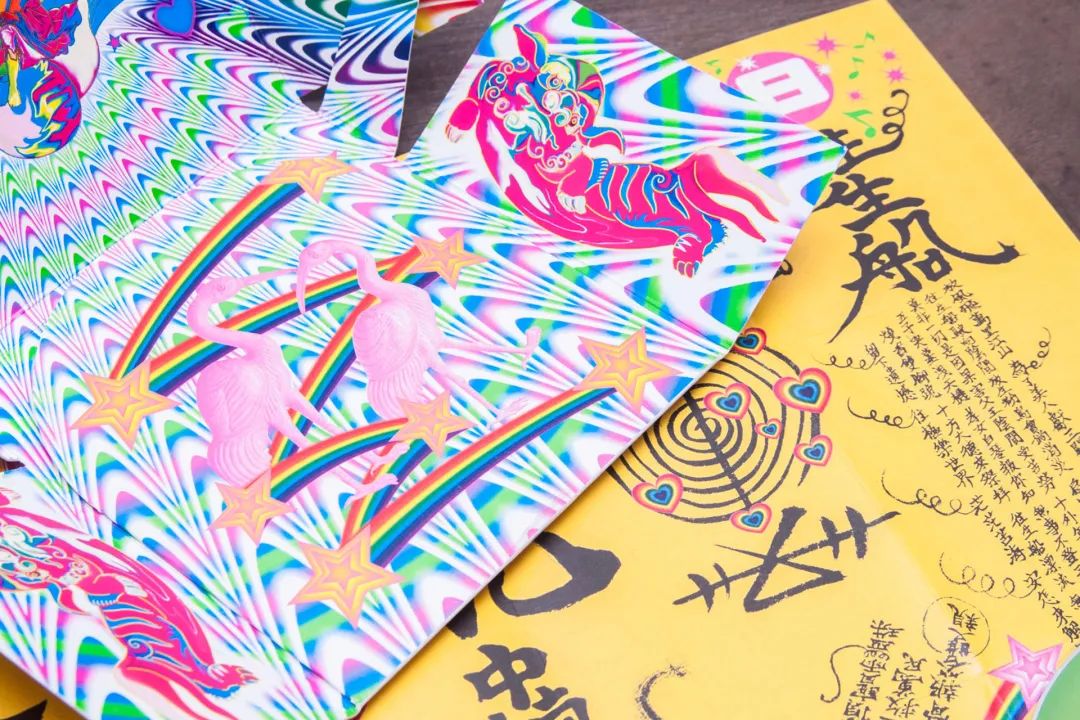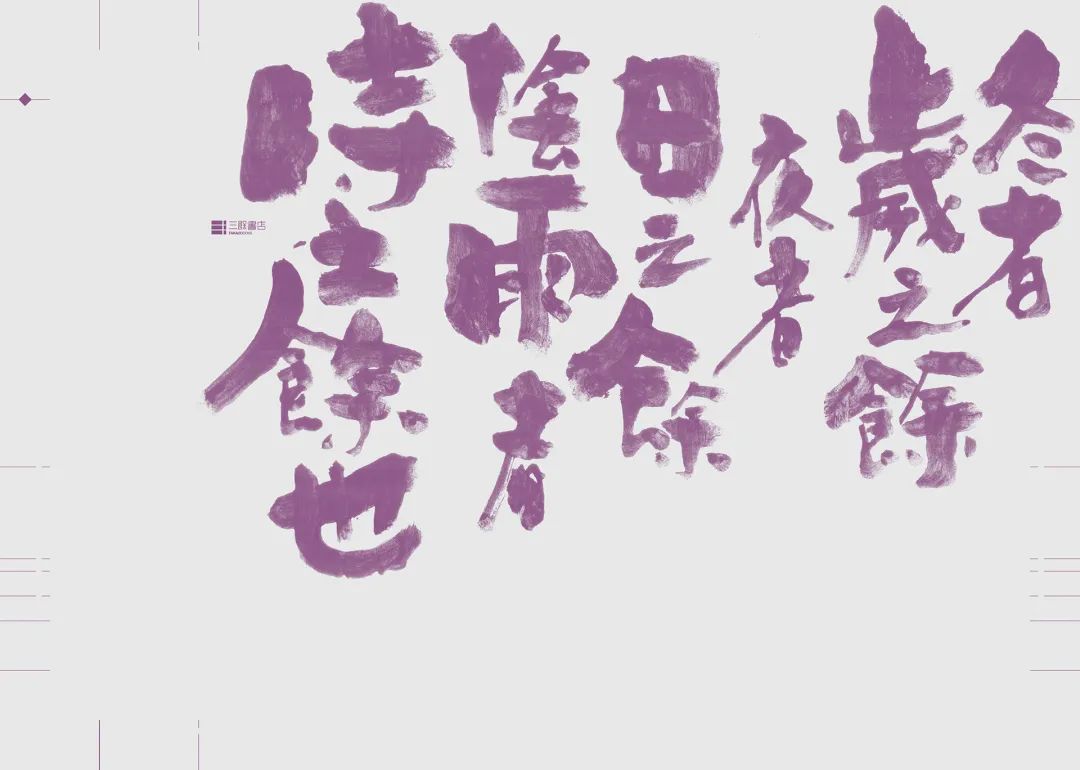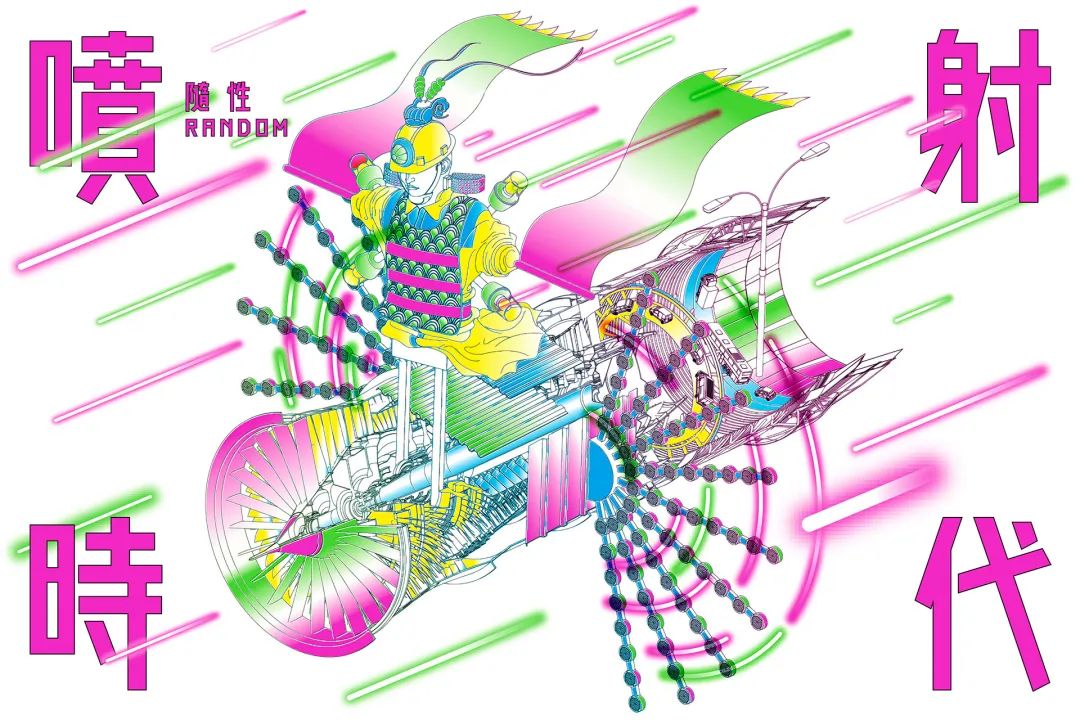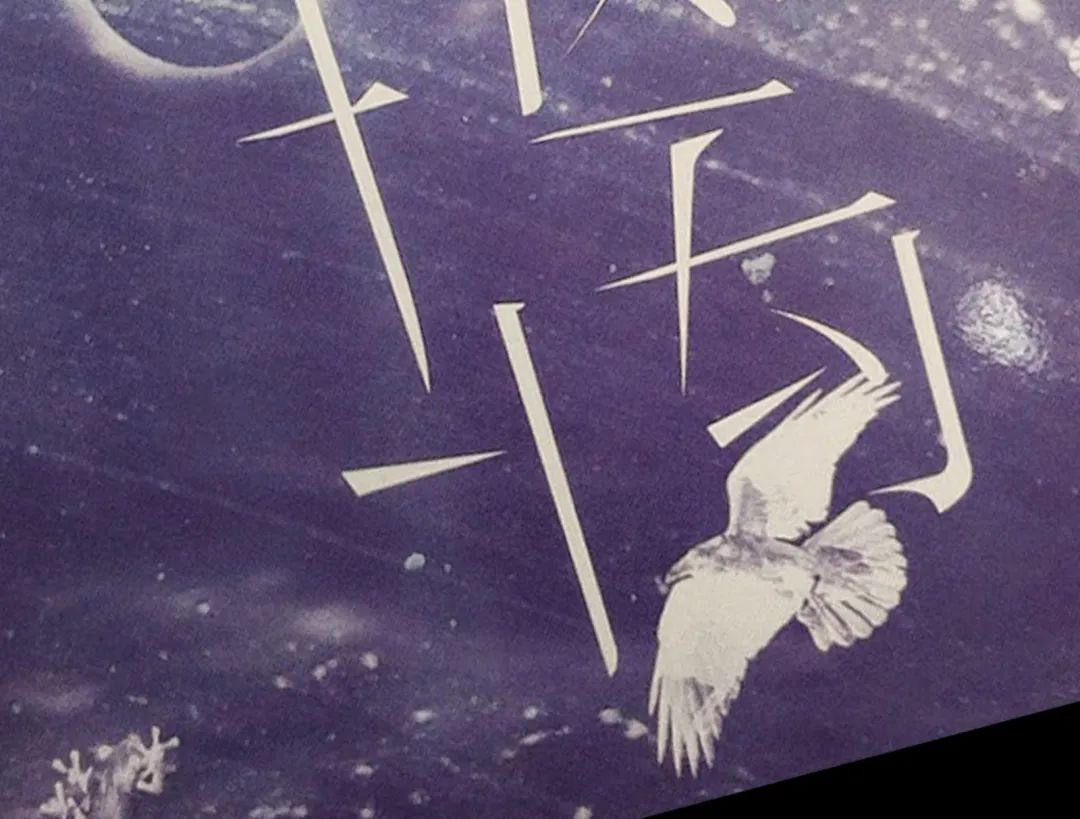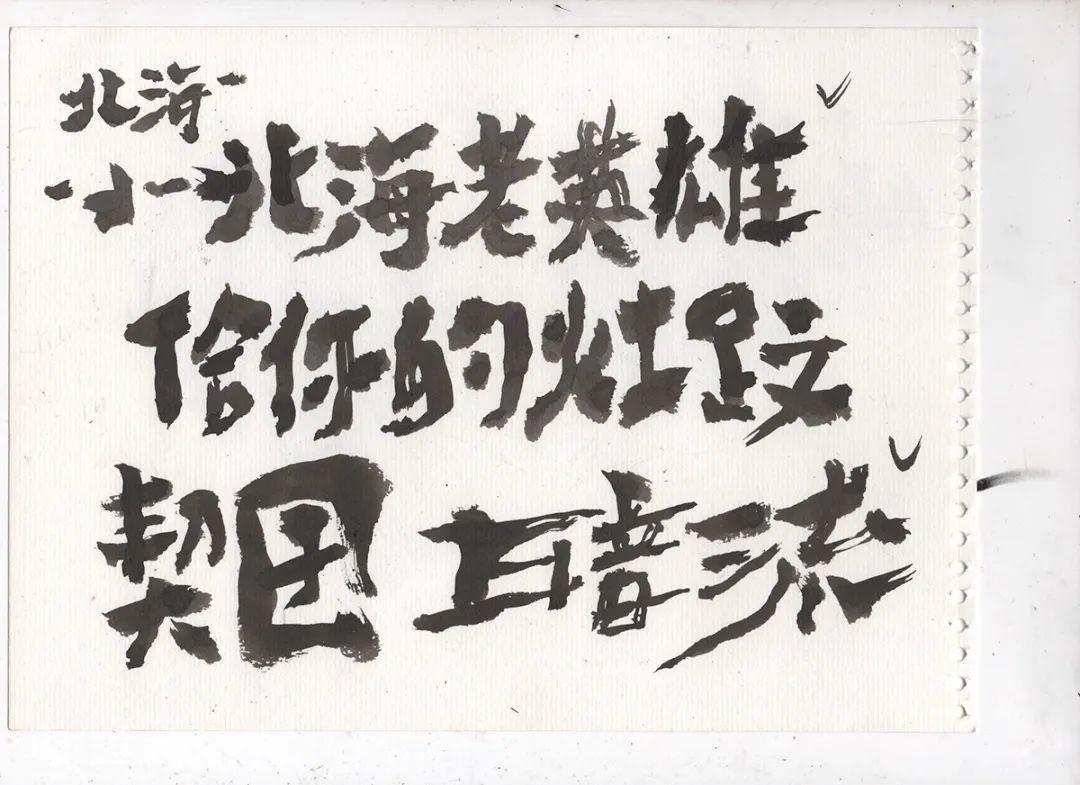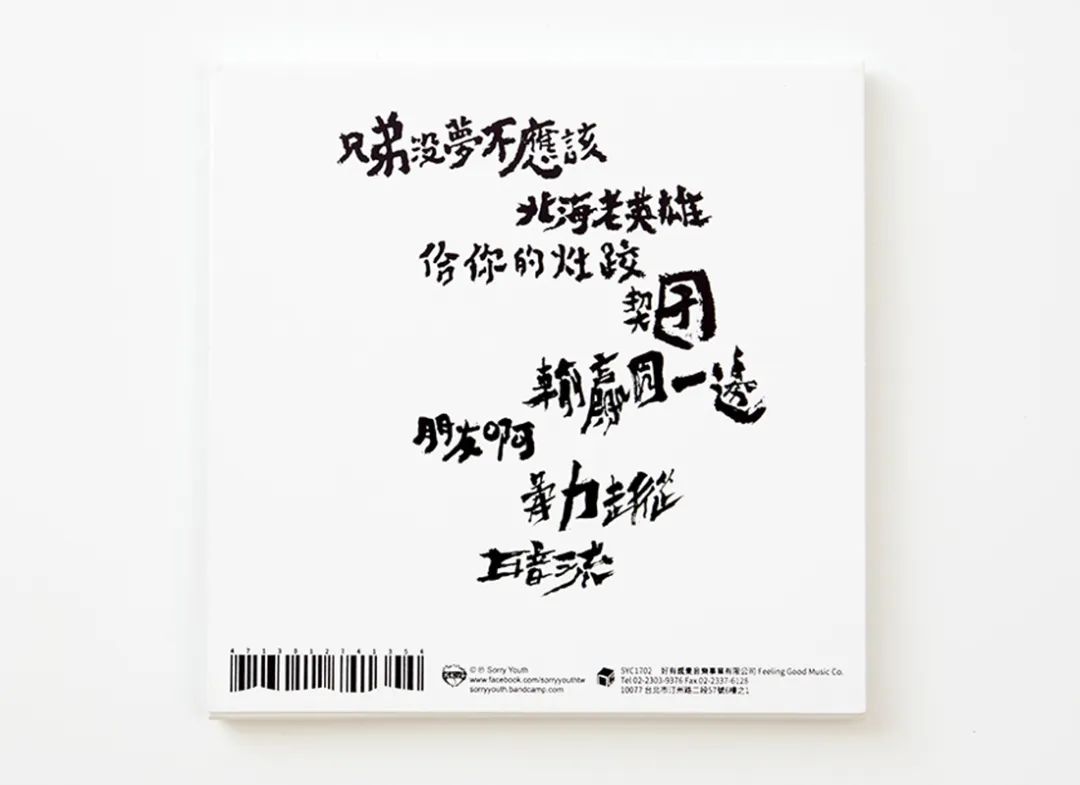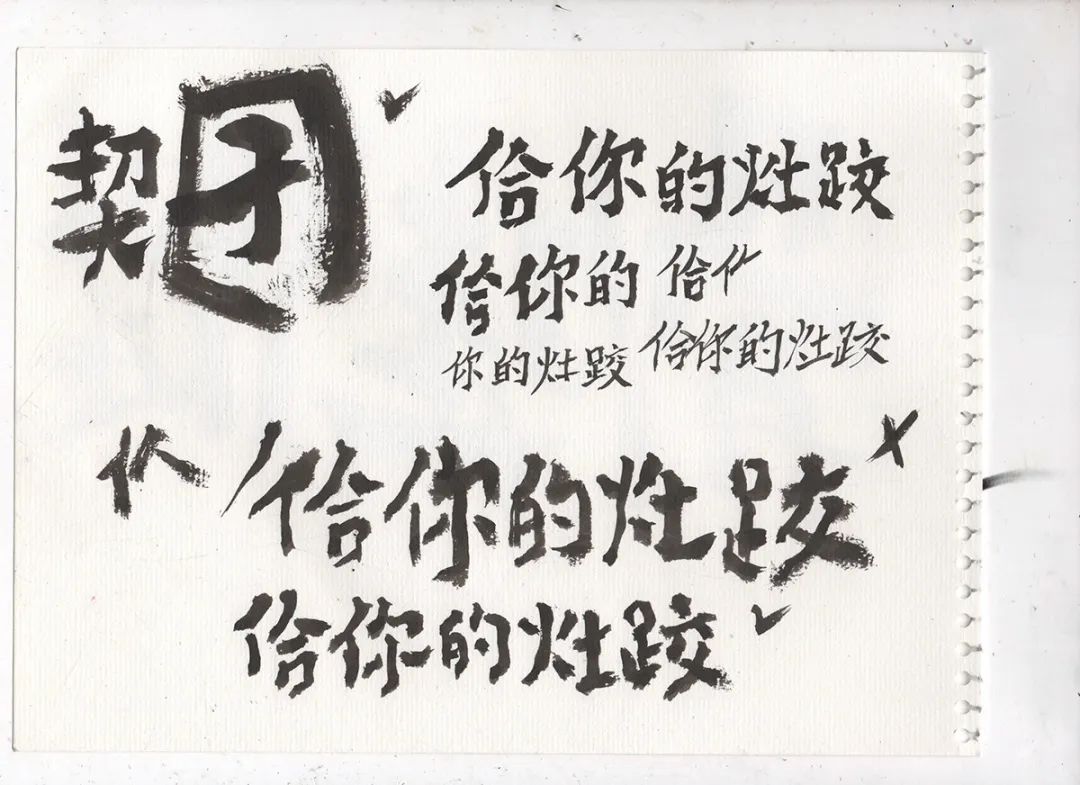
超大的字号、艳俗的色彩,他怎么这么秀
头顶板寸,脑后长辫,他身着大开三扣的花衬衫,脖子上的刺青会随着走路的摆动而忽隐忽现,我不说他是设计师的话,大家肯定会误以为是那条道上混的兄弟。这位张扬又粗犷的男子以他独特的「台味美学」混迹设计圈,他就是廖小子(本名廖俊裕),下面我们就一起来认识认识这个,痞气十足的设计师吧。
设计师简介
在台湾嘉义长大的廖俊裕,他的父亲是当地建筑工地的一个小型工程承包商,所以家中常有工人走动,那时廖俊裕的父亲对他说,要称这些人为「师傅」。打小起养成对手艺人的敬意,这让廖俊裕对劳动阶级多了一份深厚情感,这份难以割舍的感情,也成为他从台湾草根文化汲取创作养份的源头。
廖俊裕深受父亲的影响。现在袒露胸膛只扣一半花衬衫的打扮,也是耳濡目染了父亲的习惯。
从小他喜欢看功夫电影「好小子」,因此父亲开始叫他「小子」。就这样叫着叫着「廖俊裕」变成了「廖小子」。
高三时的一个领悟,使得廖小子背弃了父亲对他成为一名律师的期望。这可不得了,因为他们家族里有从事法律的亲戚,廖小子成绩也不错,做父亲的当然希望儿子能跟着去走法律的康庄大道。
然而廖小子执意要选美术系,因为这件事父子俩吵得非常凶,还在家里大打出手。两人拿着大型立式电扇互砸,最后「黑带三段」的儿子打赢了老子(真刚啊~)。无奈劝说没有,渐渐的廖小子的父亲就默许了这件事情。
有一次,廖小子的父亲喝醉了说:自己曾经也热爱绘画,但是没能坚持自己的理想,被你的祖父给劝退了,如果你真要转念美术系的话就要学好,要有决心在这条路上闯出一片天,也圆父亲的一个梦,自此廖小子就开始了他的设计之路。
高中毕业后,廖小子顺利的考上了高雄师范大学 ·美术系,但因家庭条件不好,连买画材的钱都没有,为了自力更生廖小子大学时就开始接活。跟大部分新手设计师一样,一开始接的都是些街头小广告,DM单之类的设计项目。那时的廖小子也喜欢日系、大气简单的设计,但是能发出这种委托的客户,想要什么东西大家心里都有数。
完成项目后,客户一直要求改稿,希望字可以在放的大一些、颜色要鲜艳的、图要修得很沙龙、在整个玫瑰顺带一个外框与阴影。
人在屋檐下不得不低头啊,最终廖小子选择了妥协说“既然打不过那就加入他”,而且要做就要做到自己满意为止。久而久之「把字放的很大」、「挑战文字装饰的可能性」等手法就变成了廖小子做设计的方式。
在一次的采访中,廖小子带著几分自豪的笑了笑说:后期因为习惯把字放的很大,使得我成为了第一位,让客户提出缩小文字字号意见的设计师。怎么说呢,见字如见人,不气派就无法展现真正的廖小子风格。
台味美学风格的诞生
廖小子出生在劳工阶级的家庭里,从小就会接触到那些庙宇啊、招牌啊、卡车喷漆之类的附有庶民风格的东西。成为设计师后他在思考「我要找什么东西来做?」、「我可以怎么去做?」的时候,就会想到这些东西。
而从自己的生活、成长背景去思考方向,也是美术大学给他的教育。廖小子说:我就是在那样的环境里长大的,所以我自然而然会运用那些元素,我也一直在做这样的事情。
除了环境因素外,还要归功于廖小子的一个爱好,他非常喜欢看国家地理频道、Discovery,而看的正起劲突然插播广告,是电视台的一贯作风。
廖小子被迫一直看、一直听那些「哇!赚大钱了!」之类的夸张又怪异的广告,他本人虽然不喜欢这些东西,但转念一想既然被迫观看,不如仔细研究一下编排和设计,深入了解后他发现,这些广告的风格不仅原创,而且颇具台湾味。
自此之后,廖小子开始观察那些看似凌乱又不修边幅的路边广告设计、街边喷漆涂鸦、霓虹招牌以及看板等非常具有地方特色的“设计作品”,并且不断尝试在自己的作品中融入这些“艳俗”的东西。久而久之专属于廖小子的台味美学,就这样诞生了。
「街头涂鸦」给了廖小子书法启蒙,「模板喷漆」教给了廖小子标准字,「大卖场广告」给了廖小子排版灵感,最后「庙宇装饰」成为了廖小子做唱片装帧用的素材。他说:当我有能力扛着劳工美学做设计时,就不会轻易放弃。
获得荣誉
桃园设计奖
第29届金曲奖「最佳专辑装帧设计奖」
2018金点设计奖
另一重身份
除了是平面设计师、视觉艺术家、策展人以外,廖小子还是「拍谢少年乐团」的第四位成员——虱目鱼头人。板寸头大马尾,身着花衬、衫脚踩人字拖,这很摇滚!!
而乐团出的所有专辑,基本上都是由廖小子亲自设计的。其中《兄弟没梦不应该》这张专辑使廖小子勇夺了第29届金曲奖「最佳专辑装帧设计」的这样一个奖项。
作品解析
比冥王星更远的地方
本书描述一位陪伴癌症晚期母亲的少年,与一个拥有幸福家庭的历史老师,他们都把生活中所积攒的压力藉由创作小说的形式给抒发出来,只不过他们没发现各自在书写的正好是对方的人生故事。他们在撰写彼此的人生,延伸到我们可以改变对方的人生,直至我跟你的界线开始模糊……因此廖小子推想所谓比冥王星更远的地方,应该是个似曾相识却未曾见过的场景,就像两位主角各自的所在——平行的两个现代。
封面使用了一张现代世界的照片,角度做了适当的调整倾斜了一下,这么做是为了让看似熟悉的场景变的陌生,像是飞行中翻滚俯视着地面,或是成了宇宙中的另一颗行星,反正我们远离了认识的地球。
书腰选择了一张模糊的,某个长满枯树干的荒漠照片,搭配刀模轧形突显崎岖感,虽然照片中所有组成要素都是我们能够理解的,组合后却成了一副陌生景象,就像是小说中互相虚拟的世界观:平凡熟悉到不行的生活环境,突然被一个莫名的造物主摆弄,使得一切开始模糊崩坏。
作者觉得尽管人与人之间,没有被什么牢笼牆壁区隔开来,但在这个信息时代,资讯流动的实在是太快了,以至于来不及被人消化、关心,这使得我们之间尽管只隔著空气,但这空气却好像浓雾,像透明的屏障,或是一大片玻璃。廖小子心想:要是能将这样的世界呈现出来就好了!但预算内可用的做法都很难创造出玻璃般的质感与厚度,所以廖小子选择了一个相对便宜的做法,那就是在图片上直接做出层次。
为了视觉化这个层次感,廖小子思考了很长时间,最后想起下雨天被溅上泥土的玻璃,他说或许这就是我想要的。开始设计之前,廖小子郑重地对阳台上的植物道了个歉,然后狂挖它们的土,撒到买来的压克力板上后,保持在放进扫瞄器前不要掉落太多,经过一系列的实验,终于出现了理想的效果。就是我们现在所看到的这样,好像被雨淋过后七分干,又像被几个路人不经意抹了几下,最终形成了这样一个独自沧桑的玻璃世界。
在这本书有三种不同的款式,因为廖小子在书中读到了多种情感,他打算都展现在书封上。第一款会有海马在里面游动,那是一种厮守。第二款会有乌鸦,它在日蚀中不断追寻,自己看不见,也无法被找到。第三款则是扑向光源的飞蛾,凭著自己的本能,理智往往都是之后的事了。
最后就是这个标准字了,廖小子想要做一个玻璃意象的延伸,他觉得最适合的关键字就「碎裂」,像是一种破冰的希望,情感终于开始传递,这假如直接以图像呈现,视觉感受很容易变得暴力激烈,所以决定用标准字来诠释「碎裂」,廖小子把「玻璃」两字的笔画修得更加精简、细致,后在把笔划拆开,破坏文字向心的结构,让它们看起来像裂痕,也像碎片崩开的瞬间。
惡之華 I
廖小子说:一直以来,我都相信「物极必反」这个道理,跟「阴阳」二元律这个概念很像。比如,你追到了一个很漂亮的女朋友,会暗爽觉得自己很有面子,但却得常常担心苍蝇,「爽」与「烦」并存。这也可以用来解释《恶之华》,诗中描写得越加丑恶不堪的,其实越是击中人心急欲隐藏和掩饰的。「恶」以至极,反而诚实;极恶,却也极善。我想呈现这样二元性的概念在一体之中,同时也要包含相互对立的特质。
为了表现出这些感觉,廖小子采用了描图纸作为书衣,因为描图纸的半透明特性,会让「书衣」与「内封」两个部分既可合二为一,又可分别独立,很适合表现出二元性这个概念。
《恶之华》中描述的,尽是些人类不敢正视的欲望,之所以不敢正视,往往是因为未知——因为不了解而产生恐惧,恐惧了,就更不敢去触碰,进而指称其为「恶」。所以,在书衣上廖小子尝试放了朵花,并且扭曲它,拉扯它,让它在尽可能看着像花的同时更肆意地延伸自己,让它凌驾于常态的感官逻辑,让它变得难以辨识,于暧昧之域狂野地绽放,独具侵略性尽显凶狠。
而在「恶花」书衣之下,放了一张波特莱尔的照片,他的眼神充满了摄人的力量,好像一旦与之四目相交,便会被他的目光直直看进内心深处一般。针对这个力量,廖小子做了许多不同的尝试,发现都不及这照片本身内蕴的张力。想想也是,有时与其运用各种抽象,或者调动大量具象的符号来表现真实,倒不如直接让这双眼睛赤裸裸地「探照」读者,反而更有力量。
于是,一朵歪斜的妖异之花开在了书衣上,它是深邃、是欲望也是「恶」。内封的波特莱尔肖像,是真实、是坚持,他的眼神锐利如刀,又细腻如针,它是「善」。
惡之華 II
要做出超越《恶之华》的《恶之华》,这是出版社提出的要求,可是上个版本也是我做的啊,意思是我要超越自己吗?廖小子心想。正当犯愁之际忽然想起自己曾与编辑聊到他的园艺爱好,编辑说:有些花并不是用香味来吸引昆虫的,反而是发出像尸体般的腐臭,吸引苍蝇帮它们散播花粉。对啊,这就是恶之华!假如一般的诗散发香气,那波特莱尔就是将腐臭发挥到极致的诗人。
于是廖小子开始搜寻「尸花」的样貌说:越看它的造型,越觉得那就是我要的,硕大高耸的花蕊,铺散张狂的花瓣,还有令人止步的臭气,都充满了恶之华所需要的各种视觉要素,除此之外,廖小子还希望能够呈现经典的质感,所以用上一点工笔画的形态,颜色则选择了妖艳又危疑不定的特色紫。于是书衣上的尸花恶之华就现身了。
廖小子说:在标准字方面,我一直在尝试将经典、不安定、诡异这几个关键字展现出来,先将整个「恶之华」三个字的重心提高收拢,然后将文字的一些笔画,像是竖、捺或钩调整得更为尖锐,添增它们的凶残险恶。三个字好像挂在嘴角的奸笑,又有诗歌般的飘逸与洒脱。
书腰的颜色运用,延续了书衣的配置以特色紫打底,在压上大面积烫金的书名标准字,整个书腰处将书衣围起,只留花梗探出,更多的隐密与诗句,要等到翻开才能见得到。其余的特色紫与烫金,从书背延伸到两边封面封底,最后抵达折口,就像花的气味,占领了整个空间。
最后内封的部分,还是运用了波特莱尔的照片,因为可以跟前版做一个连结,但廖小子希望能再增强波特莱尔的视觉感,所以选择将他的照片放到最大,几乎只呈现眼睛部位,并且让眼球位置跟尸花花蕊重叠。书衣是尸花的腐臭,内封则是波特莱尔的摄人,两者互相呼应,连成一体。
你是穿入我瞳孔的光
假如能在封面上呈现出「透光」的感受,就太好了。但是问题在于,封面本身是一个平面载体,而「穿透」这种概念却是具有厚度的。为了呈现这样的厚度,廖小子想到了刀模打洞的方式。
封面选用250g安娜白卡纸,背面并印上反光性较强、调性却相对温柔的萤光橘红。里封则印上了多色黑,并依照书名笔划打洞。想像在一片黑暗中,由折口里面投射出橘红的光芒,浪漫地穿透封面上的笔划洞口,在呈现书名的同时,也引出内心强烈的热情。
青椒苗
该书描写一个乡下人阿炉面对近代都市化,整个乡村传统价值遭受考验所经历的挣扎。整篇文章穿插着一个事件,那就是阿炉努力地在河里寻找黑色石头,他想要找到之前被他丢进河中的黑色土地公。
经过深思熟虑的思考后,廖小子打算依靠工艺来表现出海浪的立体感。先是制作雕版模具,在通过3D技术建模做出能用于印刷的模板,据说雕版模具上的每条纹路都是廖小子本人一刀一刀刻出来的。
努力没有白费,最后出来的结果廖小子非常满意,整个海浪完全像浮雕般立体,消费者在购买后拿到手,也能感受到设计师的这份诚意。
封底的毛笔字也是廖小子自己手写的,而且手写的方式各不相同,因为每首歌的意境都不一样。整个专辑做下来,可见廖小子的用心,能得奖也是理所应当的了。
廖小子,一个不管是长相还是打扮都尽显粗狂的人,虽然痞气十足但可见他的工匠精神,善于从自身所处的环境中发现美,「灵感源于生活」一句非常抽象的话,廖小子却将它阐释的淋漓尽致,这点值得我们学习。